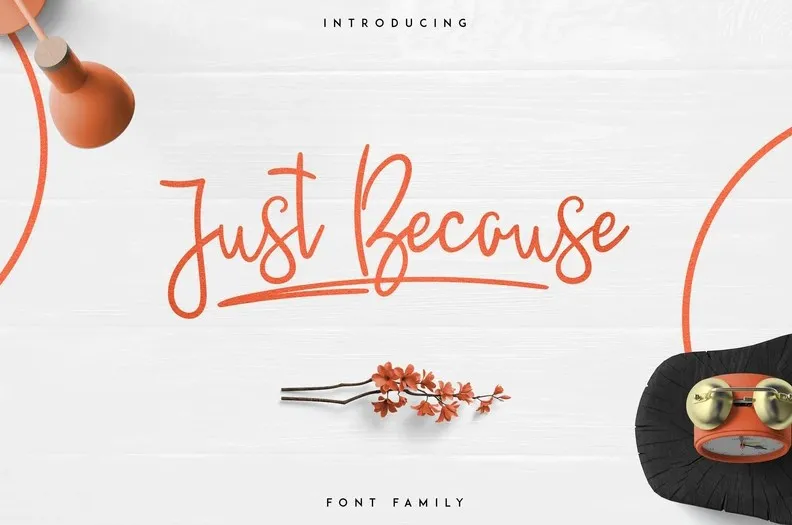
A Justbecause Script Font é uma elegante seleção de tipos escritos a mão com cinco diferentes fonts baseados em traços curtos. Ela apresenta detalhes interessantes, como as letras com swashes e estilos específicos para Adobe Photoshop. Além disso, oferece suporte multilíngue, tornando-a uma opção versátil que é perfeitamente adequada tanto para tamanhos grandes quanto pequenos. Esta fonte tem um visual atraente que se assemelha às letras escritas à mão, mas mantém um grau de precisão e controle técnico que garantirá excelentes resultados em qualquer projeto. Ideal tanto para designers digitais quanto para aqueles que valorizam a simpatia e sofisticação das fontes manuscritas. A Justbecause Script Font é uma ótima opção se você está procurando por um tipo de texto atraente, versátil e de alta qualidade. Para aqueles interessados em explorar mais sobre fontes escritas à mão, o design crítico do vp_creative_shop oferece uma experiência única que se encaixa perfeitamente no mercado de criativos digitais. Essa fonte é ideal tanto para uso pessoal quanto profissional, e tem um design cuidadoso que torna-a uma escolha confiável. Com multilíngue e suporte ao Photoshop, ela se destaca como uma opção versátil em qualquer projeto de arte digital.